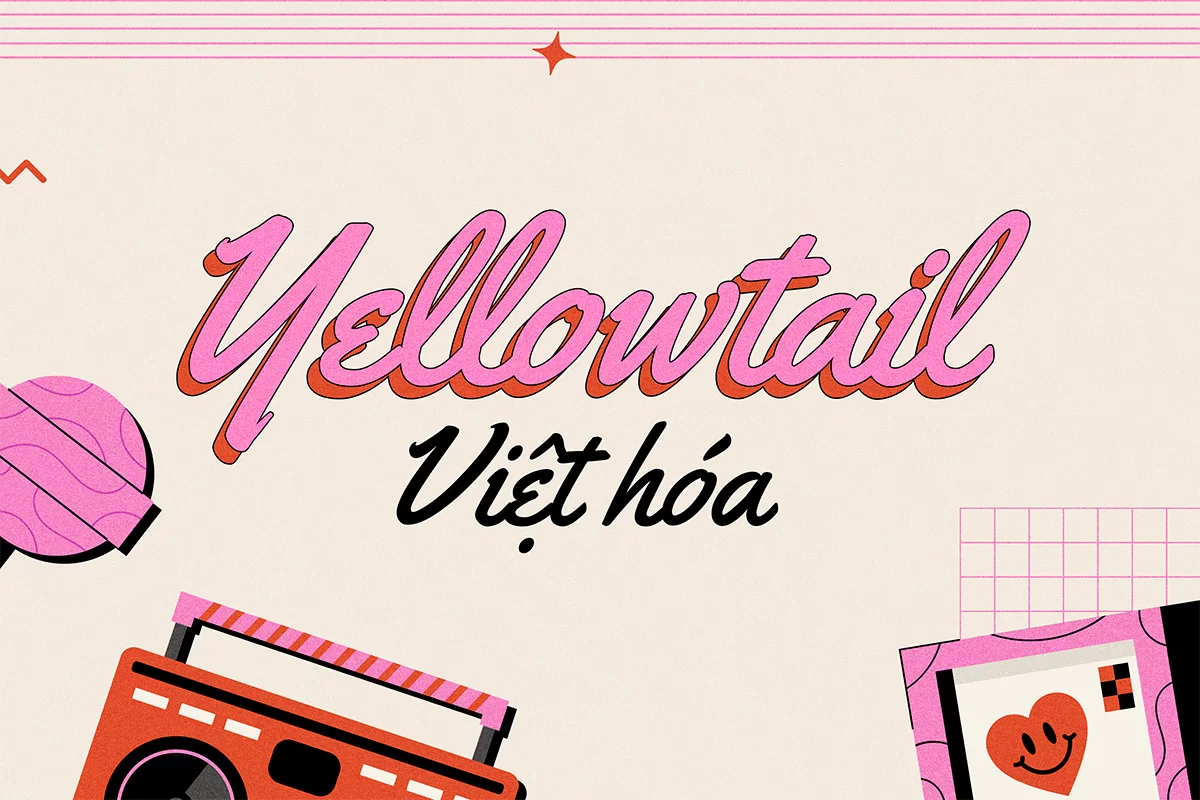
Yellowtail – Font script Việt hóa mang phong cách retro sống động
Yellowtail là một font chữ script mang đậm tinh thần retro, nổi bật với những nét bút lượn uyển chuyển nhưng vẫn giữ được độ sắc nét và dễ đọc. Được Việt hóa trọn bộ, font này hỗ trợ đầy đủ tiếng Việt với các dấu câu và ký tự đặc trưng, phù hợp cho nhiều mục đích thiết kế như tiêu đề, logo, poster, hay các sản phẩm mang phong cách cổ điển và hoài niệm. Yellowtail kết hợp tinh tế giữa cảm hứng từ chữ viết tay cổ điển của thập niên 30–40 và cấu trúc hiện đại, giúp người dùng dễ dàng tạo nên những thiết kế vừa có hồn vừa chuyên nghiệp. Với sự mềm mại và cá tính, font này chắc chắn là một lựa chọn lý tưởng cho các nhà thiết kế muốn truyền tải sự thân thiện, ấm áp nhưng không kém phần nổi bật trong các ấn phẩm của mình.